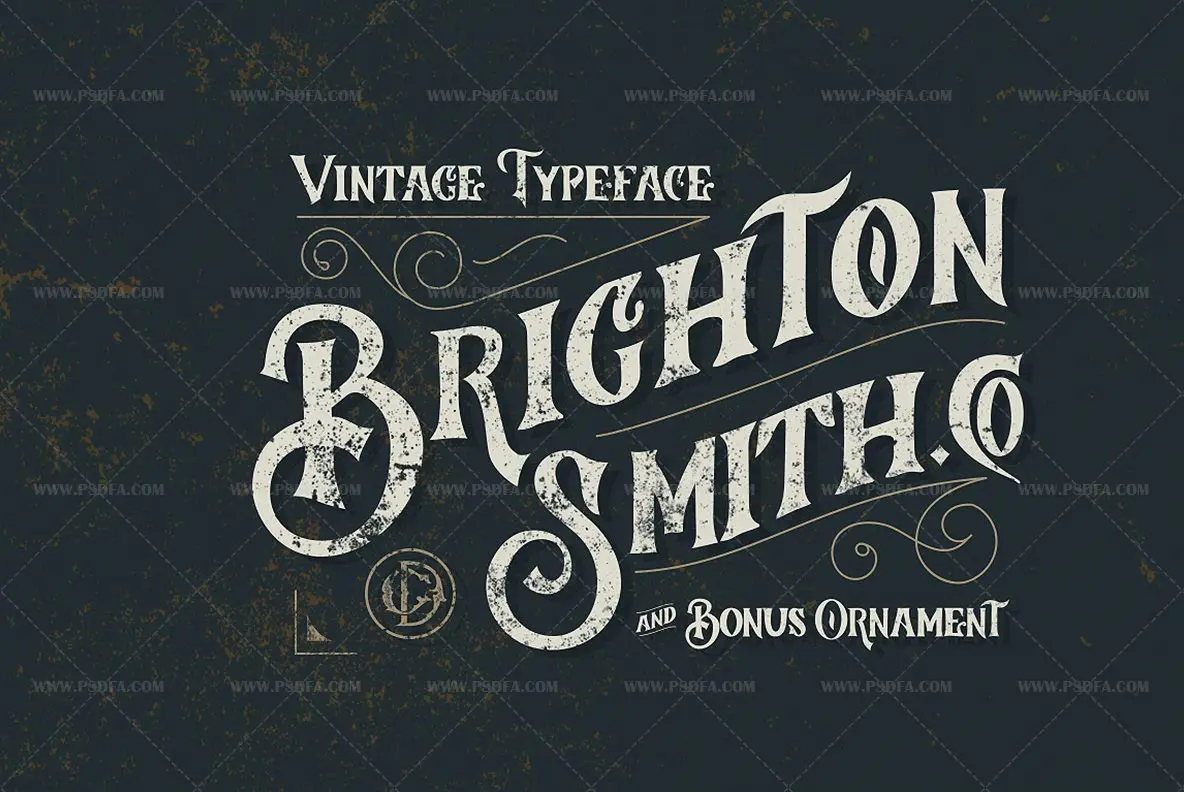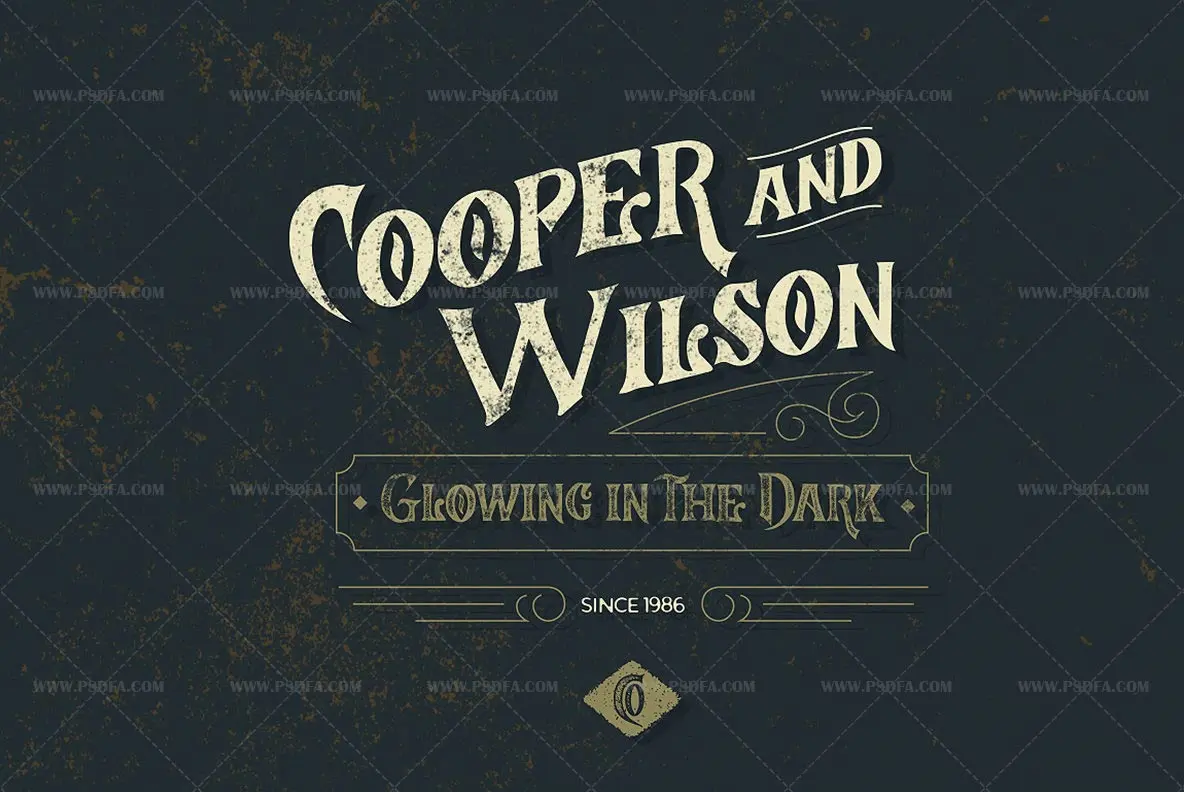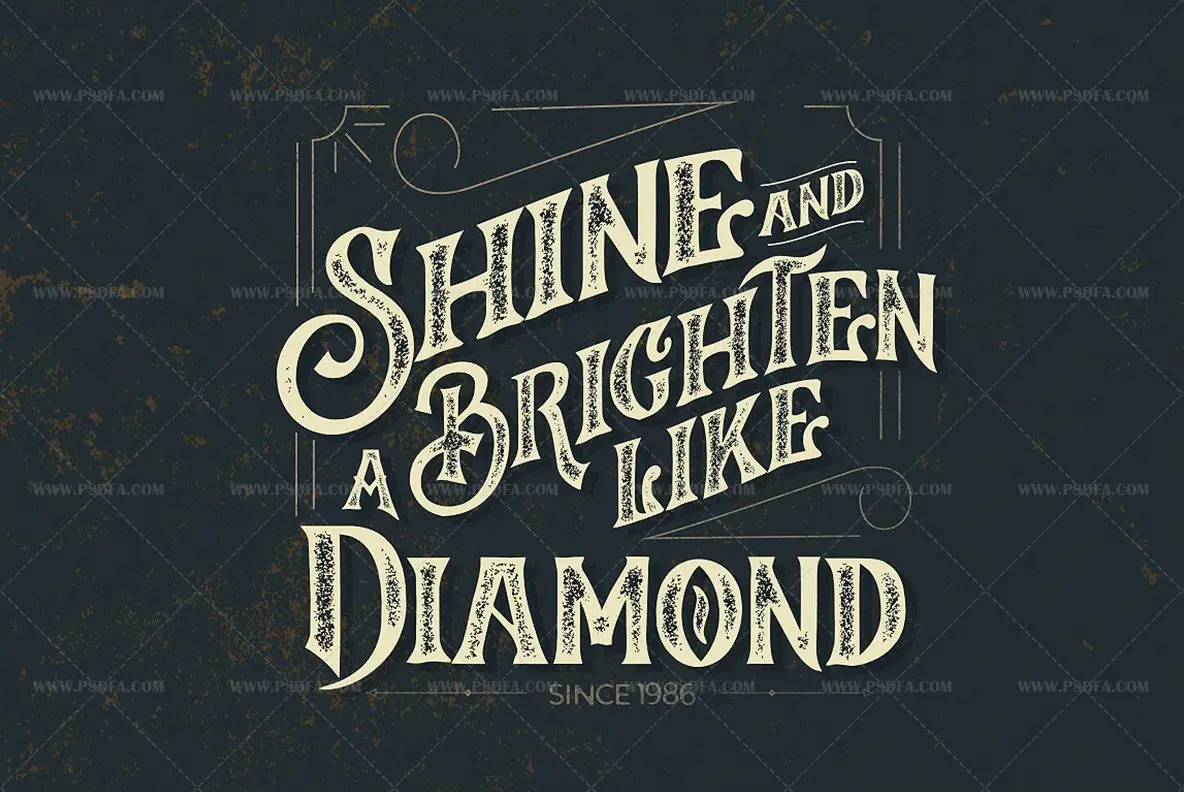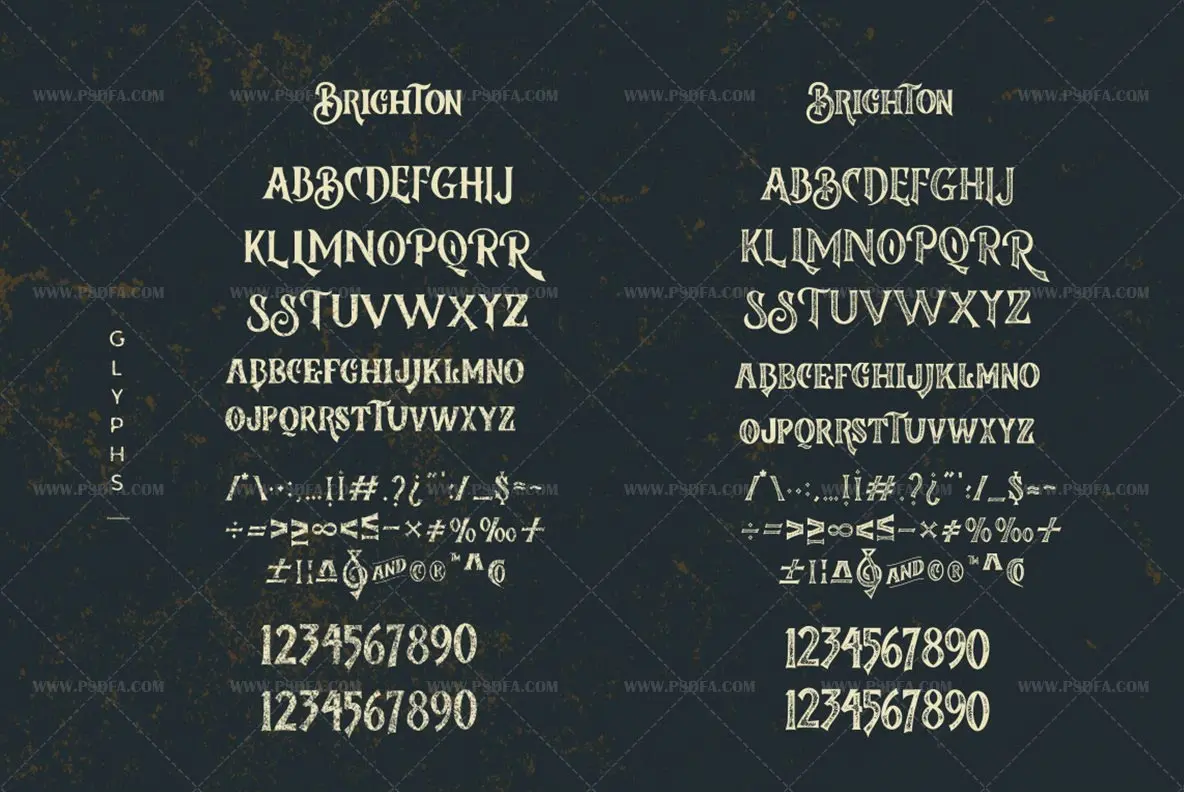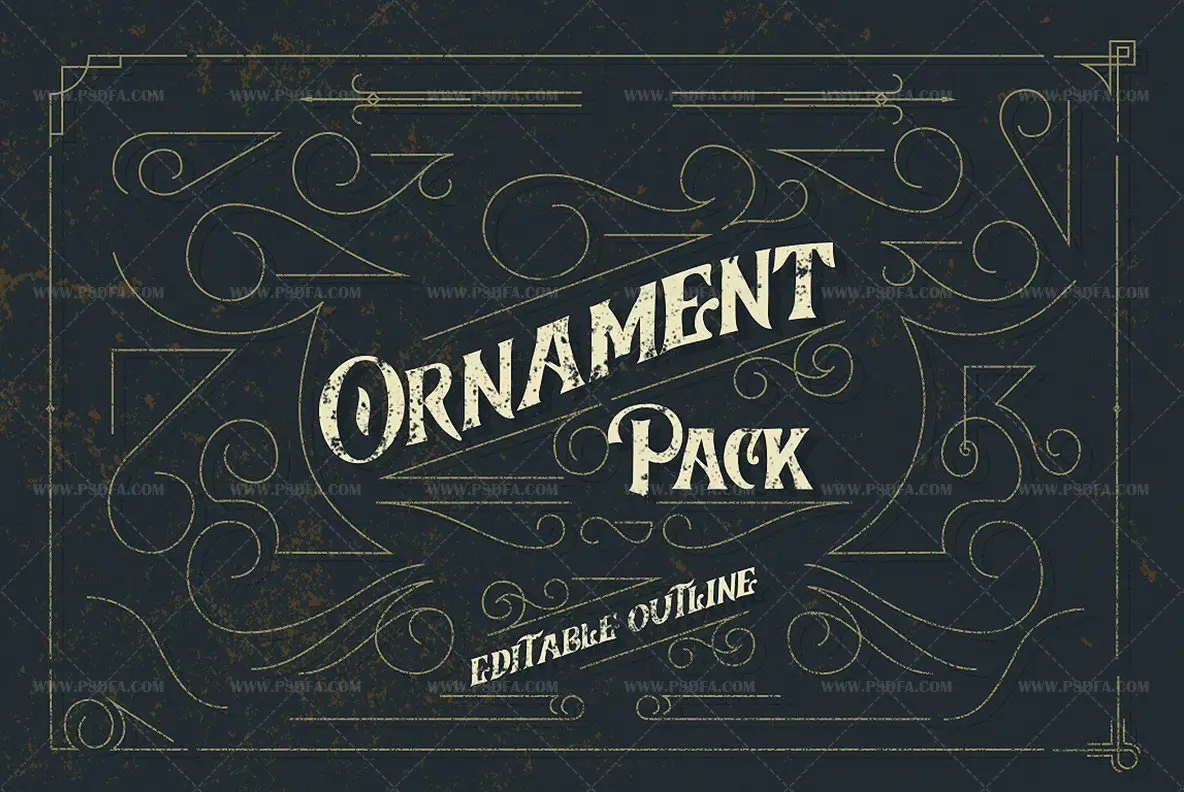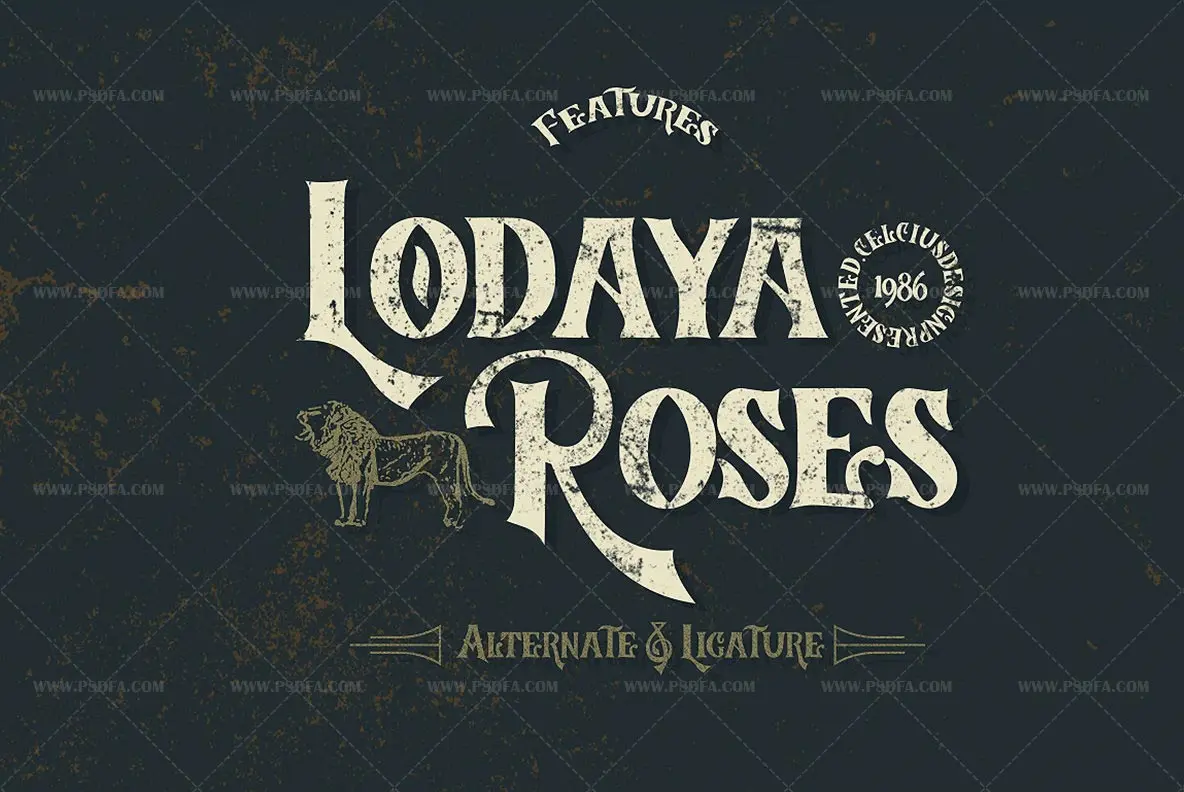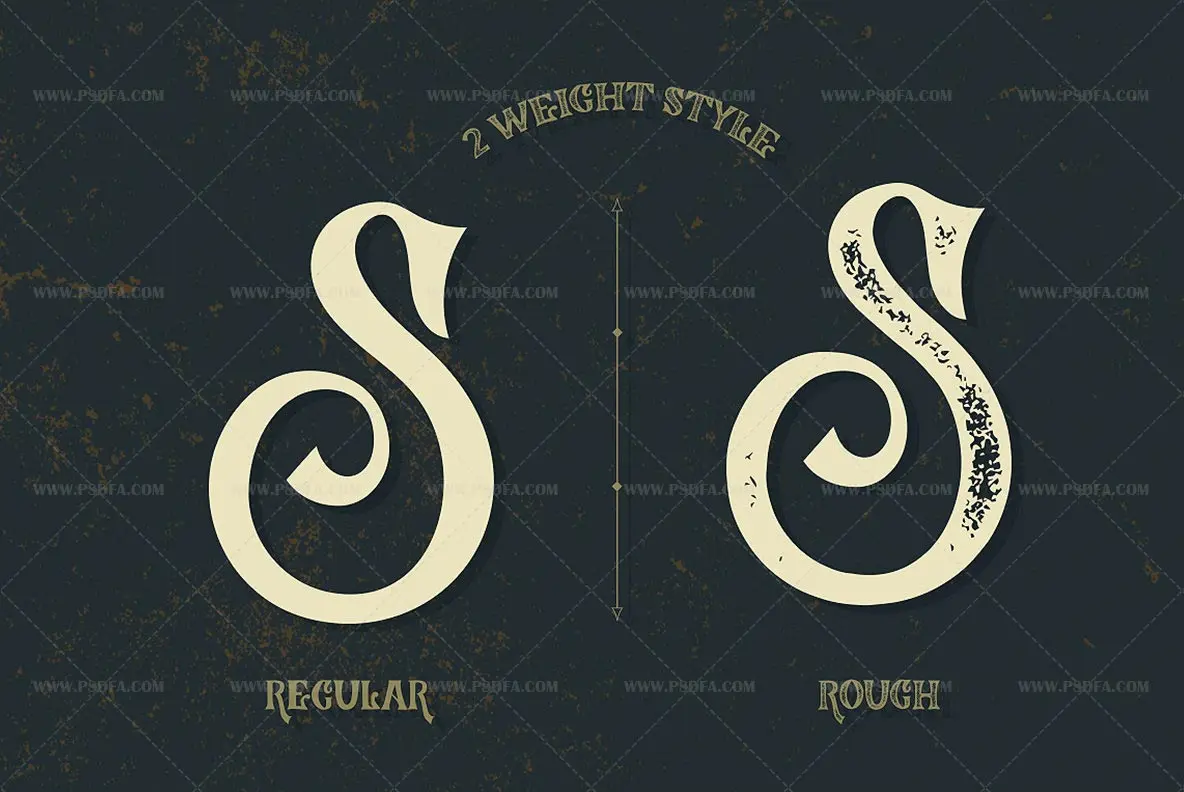
در این مطلب شاهد فونت انگلیسی Brighton جهت طراحی گرافیکی می باشید. این فونت زیبا در دو فرمت TTF و OTF در فایل فشرده موجود است که پس از دریافت و خارج کردن آن از حالت فشرده می توانید در سیستم خود نصب و از آن در تمام نرم افزارهای ویرایش متن استفاده کنید. از فونت Brighton که در سبک فونت های کلاسیک می باشد می توان در طراحی مارک و لوگوی پارچه و لباس ، طراحی ظروف ، بسته بندی محصولات تزئینی ، طراحی کارت ویزیت ، کارت های پستال و صدها ایده دیگر استفاده کرد. از نظر کیفیت نیز فونت دارای کیفیت بالایی می باشد. پیش نمایش این فونت زیبا را می توانید در تصاویر زیر مشاهد کنید. امیدواریم فونت Brighton مورد رضایت و پسند شما دوستان واقع شود و در طرح های گرافیکی خود از آن استفاده نمائید.